朋友不允许朋友使用Comic Sans。这只是一个坏主意。如果您想要一种看起来像手写的字体,请不要乱来:用您自己的笔迹创建自定义手写字体并使用它。
一旦这样做,可能性就无穷无尽。您可以轻松地将自己的笔迹用于正在处理的漫画。您可以将“手写"笔记添加到您喜欢的照片中。或者,您也可以键入便笺并打印出来,因为您懒得实际写一封信,但又想假装自己写了一封信。
这完全取决于您,而MyScriptFont可以用来创建手写内容字体再简单不过了。下载并打印PDF,然后用您自己的手写字母填写方块。扫描,上传,其余的工作将由网站完成。现在,让我们一起完成整个过程。
制作手写字体
要开始使用MyScriptFont.com。您将看到以下简单的说明:
下载PDF并打印出来。使用黑色毡尖笔填充所有字母。是的:您必须使用实际的笔和纸。您可以在页面底部找到带有重音符号的字符,但建议您使用。完成后,请按灰度扫描打印的文档。
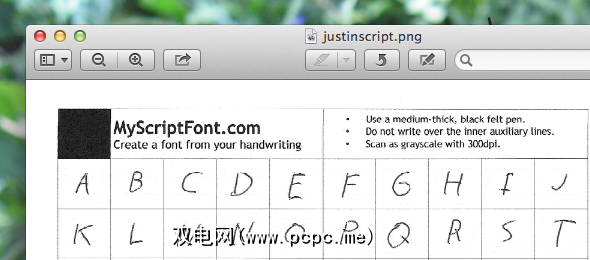
将扫描的文件另存为图像,即可开始上传了。返回MyScriptFont.com并上传您填写的表格。您需要等待一段时间;处理需要一段时间。
完成后,您将看到新字体的预览,并可以下载。我的笔迹很糟糕,所以我的字体很烂:
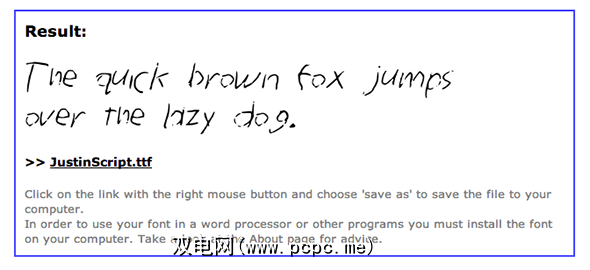
我的妻子凯西(Kathy)的笔迹很清晰,所以她的字体效果很好。检查一下:
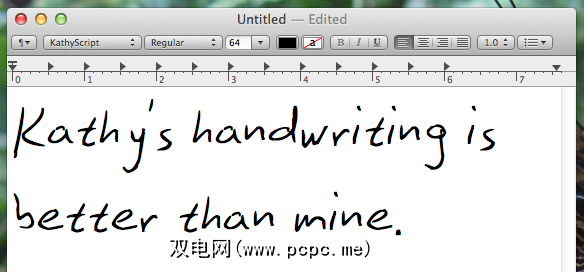
这些手写字体非常适合在文档中添加个人风格,因此请发挥您的想象力。您的笔迹反映出您的个性,因此该字体也将如此。当然,它不像您实际的笔迹那样灵活或令人动容,但它是一种快速向演示文稿或文档中添加个人风格的好方法。
结论
当然,这不是制作自己的手写字体的唯一方法:我们之前已经概述了制作自己的字体的工具。如果您想尝试排版,那么这些工具值得一试,至少要从入门入手。